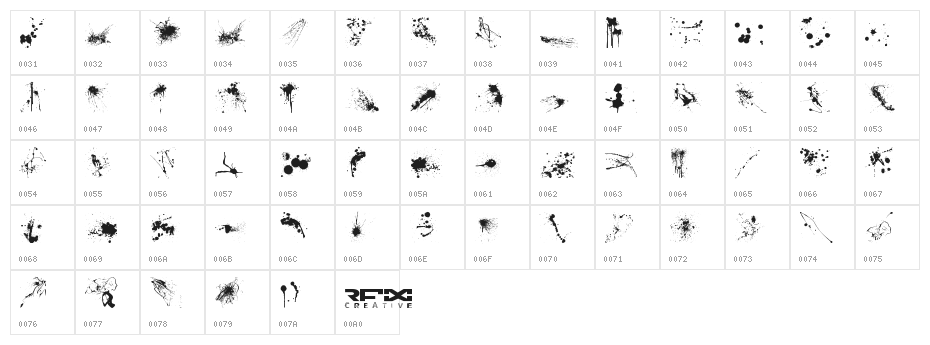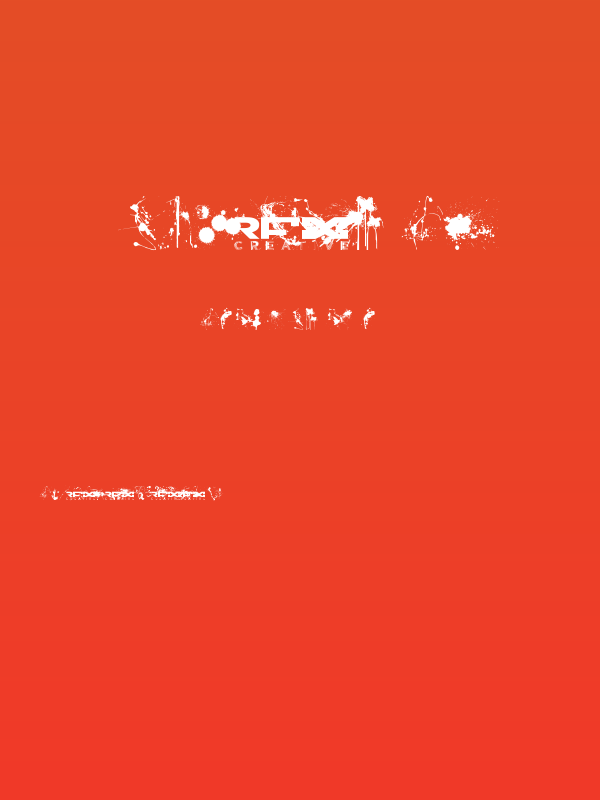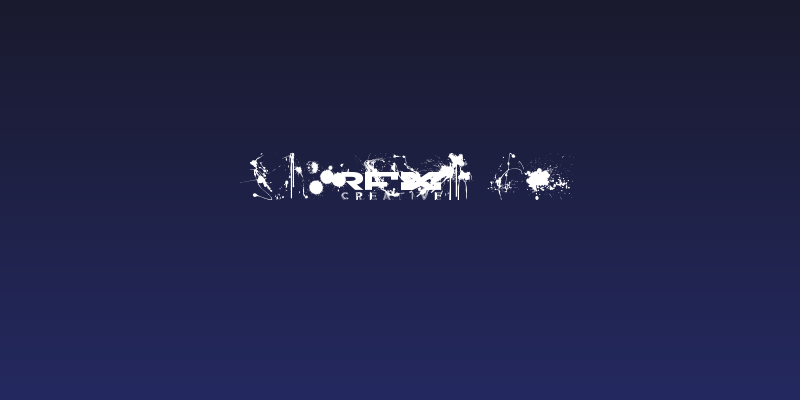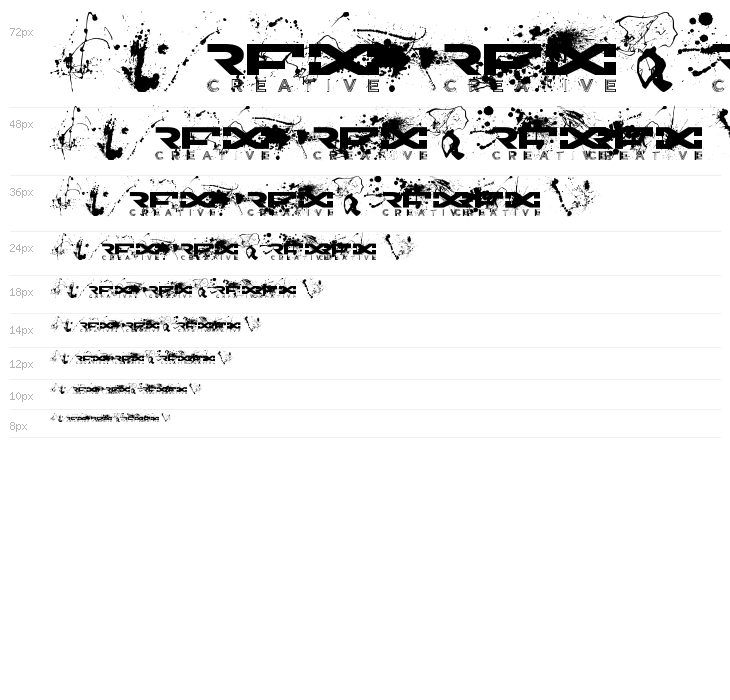
RFX Splatz Font
| Область применения | Headlines, Logos, Artistic Projects |
| Рекомендуемые проекты | Ideal for creative headlines, artistic posters, album covers, and any project needing a bold, unconventional aesthetic. |